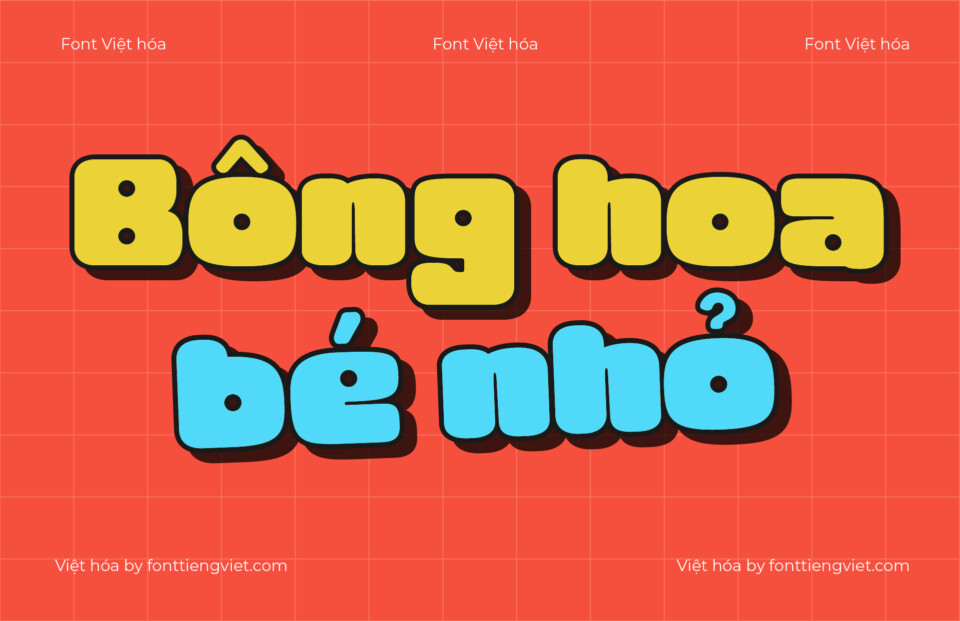
Font Việt hóa 1FTV VIP Retro Gexay
Giới thiệu về Font Việt hóa 1FTV VIP Retro Gexay
Chào mừng bạn đến với thế giới sáng tạo đầy màu sắc của các nhà thiết kế đồ họa. Trong bộ sưu tập typography hiện nay, Font Việt hóa 1FTV VIP Retro Gexay đang nổi lên như một hiện tượng nhờ phong cách cổ điển kết hợp hơi thở hiện đại. Đây là lựa chọn lý tưởng cho những ai muốn tìm kiếm sự độc đáo và tinh tế cho các dự án của mình. Khi sử dụng Font Miễn Phí, người dùng có thể dễ dàng tiếp cận với các bộ chữ đã được tinh chỉnh kỹ lưỡng về dấu tiếng Việt, đảm bảo không bị lỗi font khi soạn thảo nội dung dài.
Đặc điểm thiết kế của bộ font
Bộ chữ này mang đậm phong cách Retro với các đường nét bo tròn và chân chữ dày dặn, tạo cảm giác thân thiện nhưng không kém phần sang trọng. Font Việt hóa 1FTV VIP Retro Gexay hỗ trợ đầy đủ bảng mã Unicode, giúp các bạn học sinh và giáo viên dễ dàng ứng dụng vào việc làm slide bài giảng, báo tường hay các ấn phẩm truyền thông học đường sinh động.
Ứng dụng thực tế của Font Việt hóa 1FTV VIP Retro Gexay
Sử dụng trong thiết kế đồ họa và quảng cáo
Với vẻ ngoài bắt mắt, Font Việt hóa 1FTV VIP Retro Gexay thường được dùng để làm tiêu đề cho các poster, banner quảng cáo hoặc logo thương hiệu. Sự kết hợp giữa nét hoài cổ và sự chuyên nghiệp giúp thông điệp của bạn trở nên nổi bật và thu hút sự chú ý của người xem ngay từ cái nhìn đầu tiên. Ngoài ra, tính tương thích cao trên các phần mềm như Photoshop, AI giúp việc chỉnh sửa trở nên thuận tiện hơn bao giờ hết.
Phù hợp cho dự án cá nhân và học tập
Không chỉ dành cho dân chuyên nghiệp, bộ font này còn là công cụ tuyệt vời để các bạn trẻ trang trí thiệp mời, làm blog cá nhân hoặc trình bày các tiểu luận sáng tạo. Sự đa dạng trong cách thể hiện của bộ chữ mang đến không gian sáng tạo không giới hạn cho người dùng Việt.